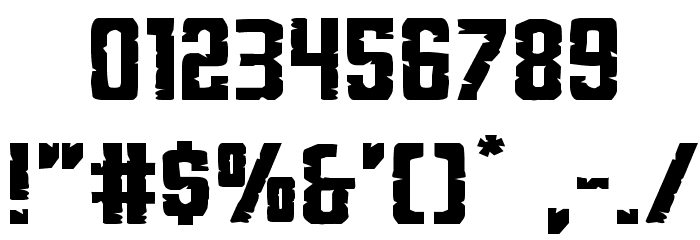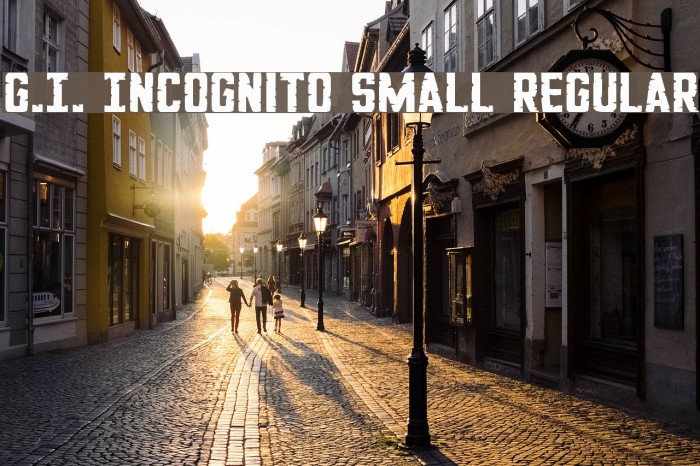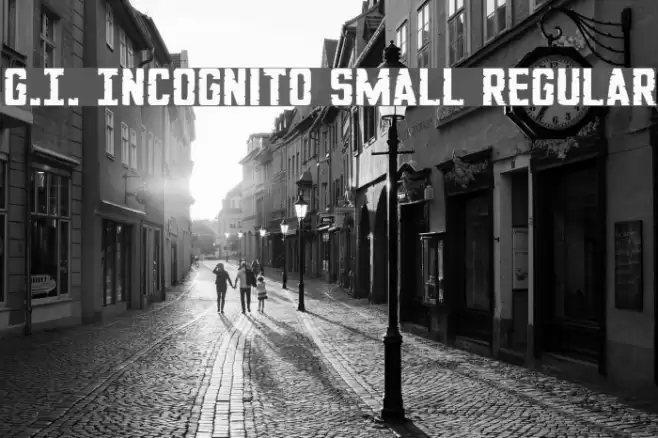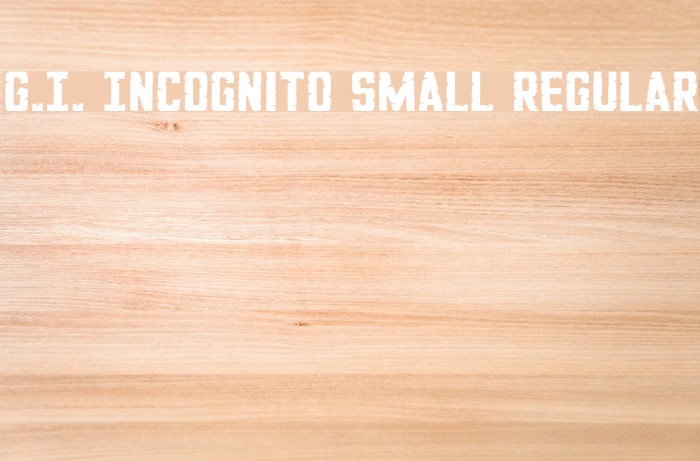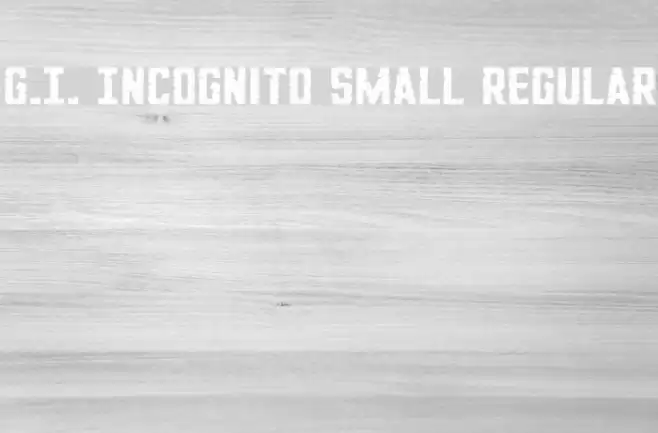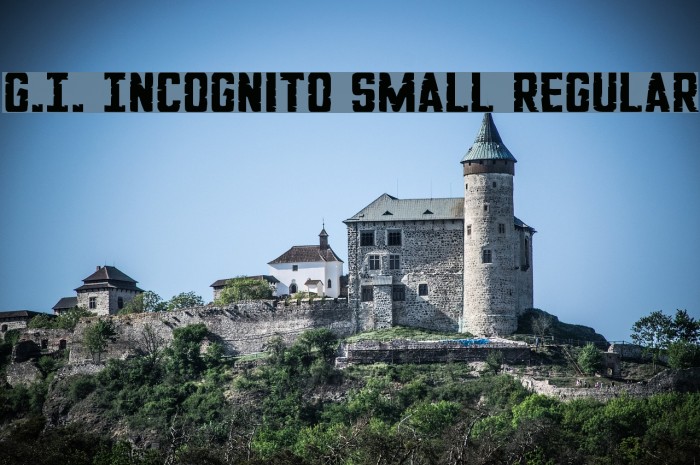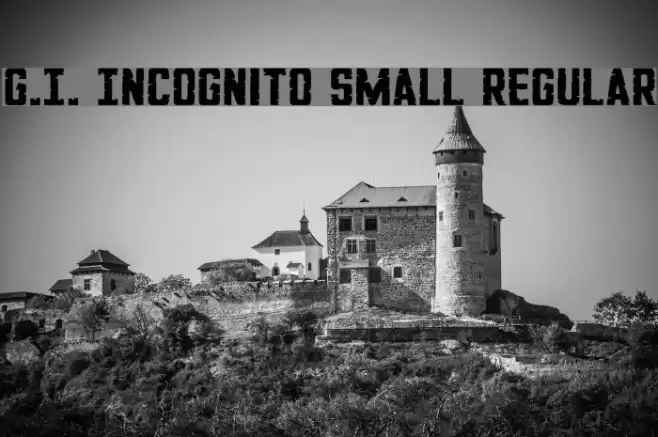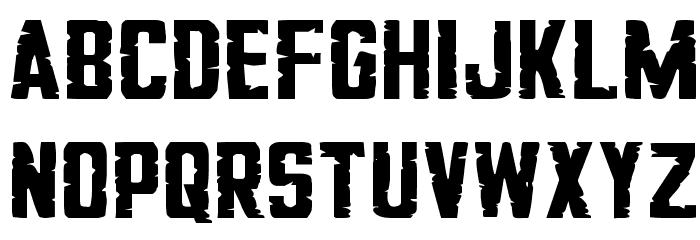
G.I. Incognito Small Regular Font
✎ Distorted Eroded
| Kategorien | Distorted Eroded |
| Gesamtstil | Modern, Decorative |
| Vorgeschlagene Projekte | Ideal for posters, album covers, branding for extreme sports, or any project needing a bold, edgy aesthetic. |